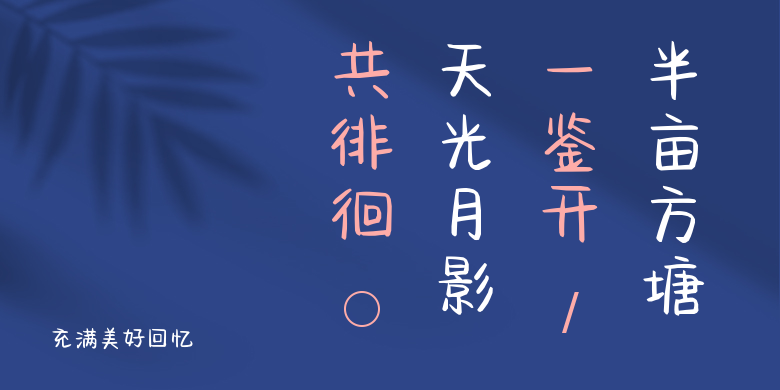
充满美好回忆
充满美好回忆,这款字体结构工整、笔画清晰,兼顾美观与易读性,适用于标题、正文、海报、包装、LOGO 等多种场景。字形优雅稳定,风格百搭耐看,适配日常排版与创意设计,让文字呈现更舒适、更具质感。充满美好回忆一笔一画,皆是细节,以均衡的比例、流畅的线条打造舒适视觉体验,字形端正大气,风格简约现代。无论是商业设计、品牌宣传还是日常排版,都能轻松驾驭,让文字更有格调与力量。充满美好回忆字体下载。